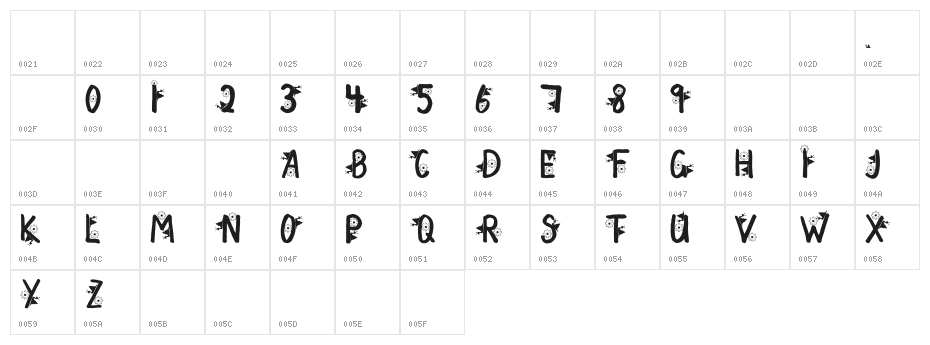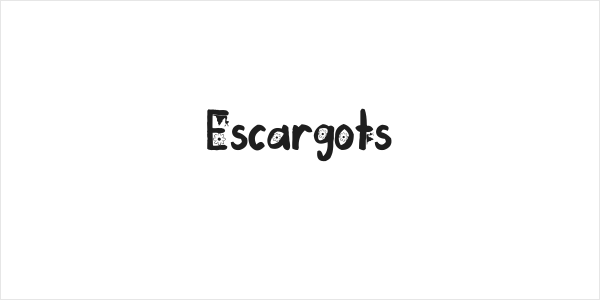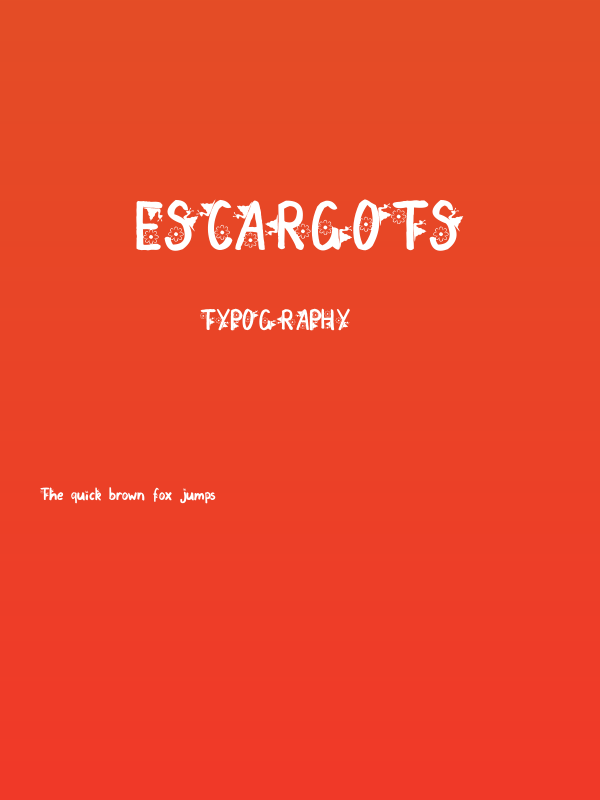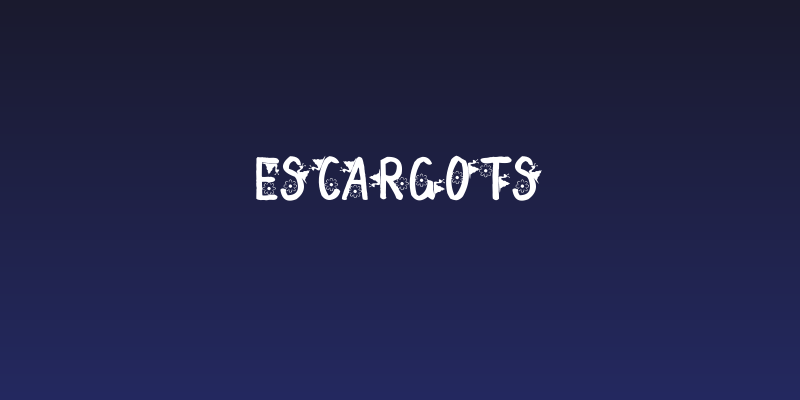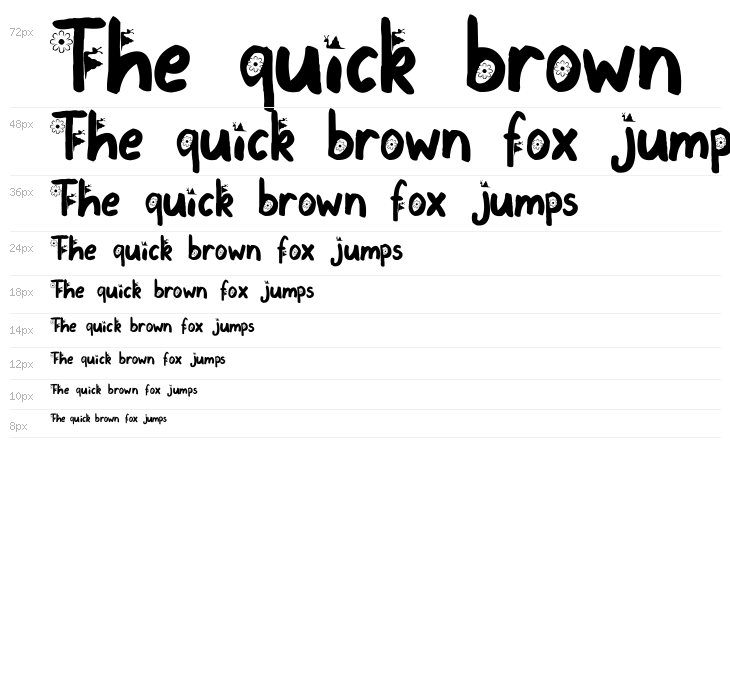
Escargots Font
| Stile generale | Modern, Decorative |
| Caso d'uso | Logos, Headlines, Artistic projects |
| Progetti proposti | Ideal for creative projects such as posters, album covers, and branding materials where a unique and artistic touch is desired. |